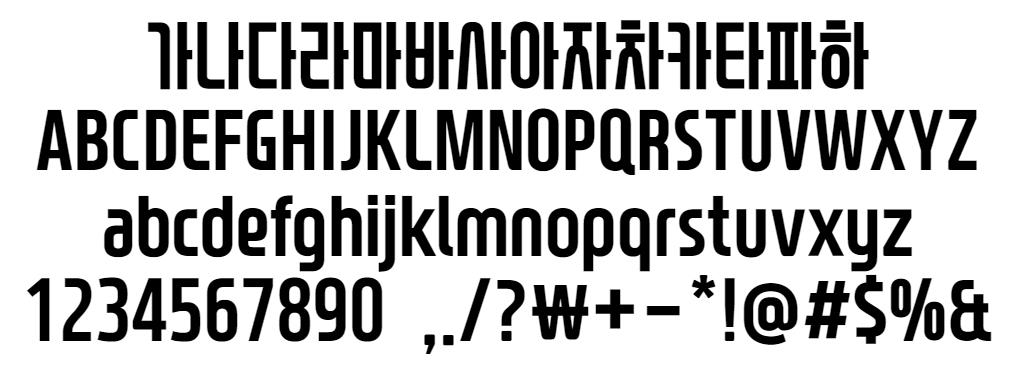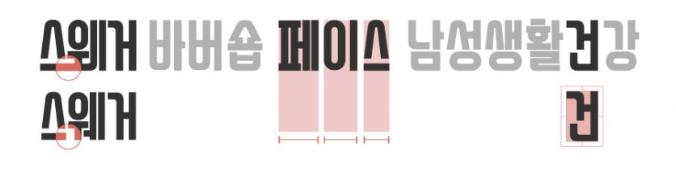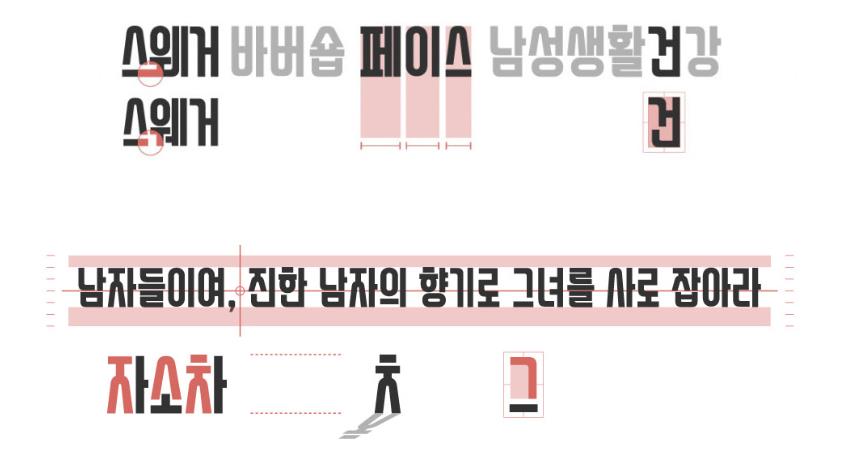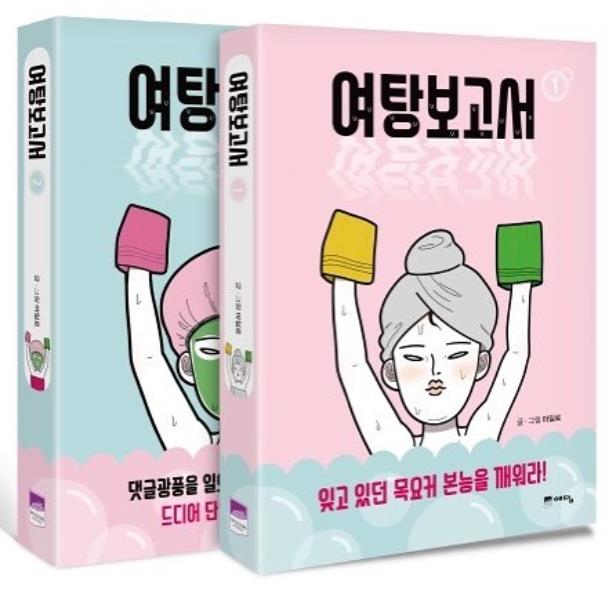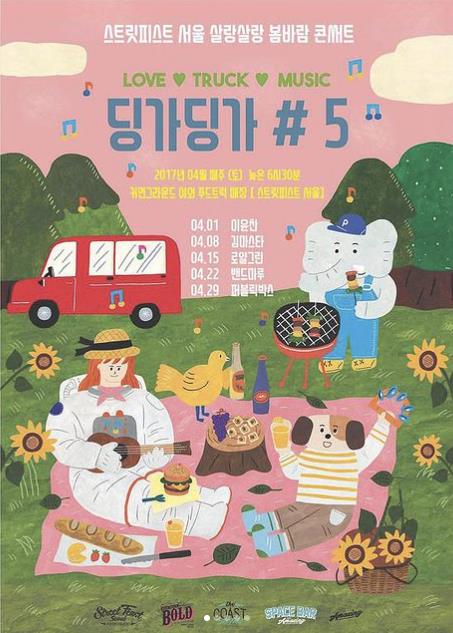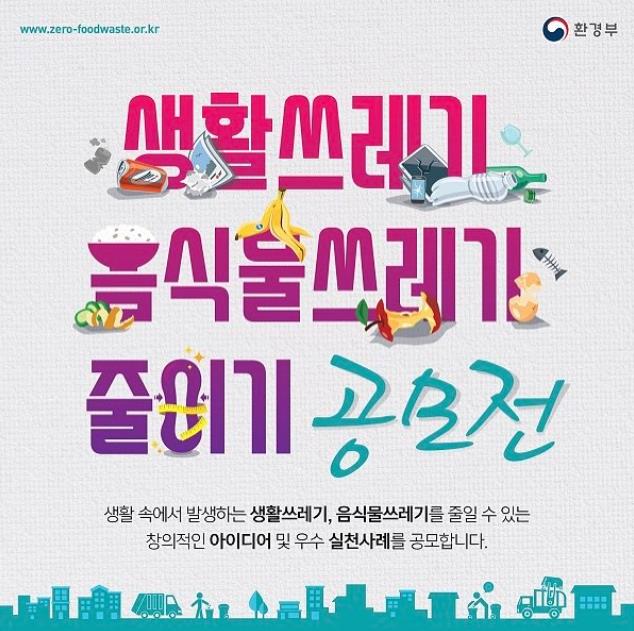
스웨거 폰트는 남성 라이프 스타일 브랜드 스웨거에서 직접 참여하여 산돌커뮤니케이션의 노하우를 통해 만들어진 서체로 제목용으로 추천합니다. 지적재산권은 (주)아트앤디자인인터내셔널과 (주)산돌커뮤니케이션이 공동 소유하고 있습니다. 스웨커 폰트는 개인, 기업 사용자를 포함한 모든 사용자들이 무료로 비상업적인 용도에 한해 사용이 가능하며, 글꼴 자체를 유료 판매나 수정, 개작하여 재배포는 금지입니다.
스웨거 폰트
특징
스웨거 영문 로고의 곡선 느낌을 스웨거 폰트에 그대로 반영되었으며, 글자의 폭을 각 그룹별로 다르게 적용하여, 획이 많은 글자는 넓고, 획이 적은 글자는 좁게 하여 자연스럽고 조화롭게 조절되었습니다.
스웨거가 추구하는 남자의 이미지가 폰트에 그대로 반영되어 ㅅ. ㅈ. ㅊ 계열들이 사람이 서 있는 것처럼 당당한 모습으로 형상화되었으며, 초성을 조금 크게 하여 전체적으로 흔들림 없이 꽉 짜인 든든한 구조도 스웨거체의 두드러지는 특징입니다.